একটি নতুন ফন্ট স্পেসিফিকেশন যা ফন্ট ফাইলের আকার উল্লেখযোগ্যভাবে কমাতে পারে
এই নিবন্ধে, আপনি পরিবর্তনশীল ফন্টগুলি কী, তারা কী সুবিধা দেয় এবং কীভাবে সেগুলি আপনার কাজে ব্যবহার করবেন তা আবিষ্কার করবেন। প্রথমে, ওয়েবে টাইপোগ্রাফি কীভাবে কাজ করে এবং পরিবর্তনশীল ফন্টগুলি কী কী উদ্ভাবন নিয়ে আসে তা পর্যালোচনা করুন।
মে 2020 পর্যন্ত ভেরিয়েবল ফন্টগুলি বেশিরভাগ ব্রাউজারে সমর্থিত। দেখুন আমি কি পরিবর্তনশীল ফন্ট ব্যবহার করতে পারি? এবং ফলব্যাকস
ভূমিকা
ফন্ট এবং টাইপফেস শব্দগুলি প্রায়শই বিকাশকারীরা বিনিময়যোগ্যভাবে ব্যবহৃত হয়। তবে একটি পার্থক্য রয়েছে: একটি টাইপফেস হল অন্তর্নিহিত ভিজ্যুয়াল ডিজাইন যা বিভিন্ন টাইপসেটিং প্রযুক্তিতে বিদ্যমান থাকতে পারে এবং একটি ডিজিটাল ফাইল বিন্যাসে একটি ফন্ট এই বাস্তবায়নের একটি। অন্য কথায়, একটি টাইপফেস হল আপনি যা দেখেন এবং ফন্টটি আপনি যা ব্যবহার করেন ।
আরেকটি ধারণা যা প্রায়ই উপেক্ষা করা হয় তা হল একটি শৈলী এবং একটি পরিবারের মধ্যে পার্থক্য। একটি শৈলী হল একটি একক এবং নির্দিষ্ট টাইপফেস, যেমন বোল্ড ইটালিক, এবং একটি পরিবার হল শৈলীর সম্পূর্ণ সেট।
পরিবর্তনশীল ফন্টের আগে, প্রতিটি শৈলী একটি পৃথক ফন্ট ফাইল হিসাবে প্রয়োগ করা হয়েছিল। পরিবর্তনশীল ফন্টের সাথে, সমস্ত শৈলী একটি একক ফাইলে রাখা যেতে পারে।
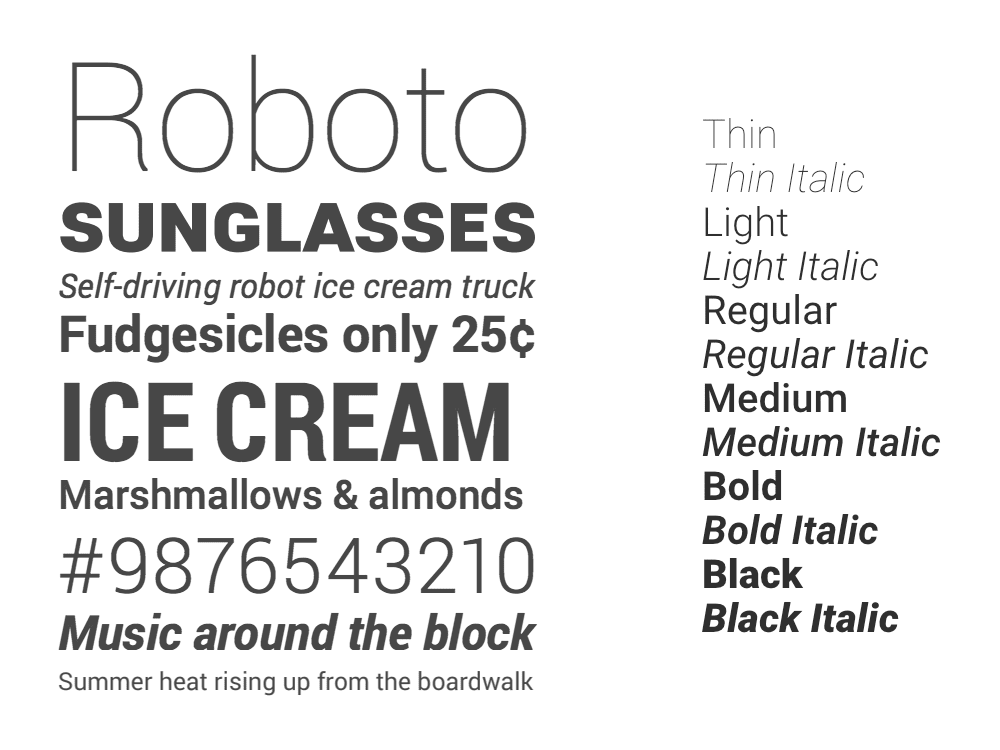
ডিজাইনার এবং বিকাশকারীর জন্য চ্যালেঞ্জ
যখন একজন ডিজাইনার একটি মুদ্রণ প্রকল্প তৈরি করে তখন তারা কিছু সীমাবদ্ধতার সম্মুখীন হয়, যেমন পৃষ্ঠার বিন্যাসের প্রকৃত আকার, তারা কত রং ব্যবহার করতে পারে (যা ব্যবহার করা হবে এমন প্রিন্টিং প্রেস দ্বারা নির্ধারিত হয়) ইত্যাদি। কিন্তু তারা যত খুশি টাইপফেস শৈলী ব্যবহার করতে পারে। এর মানে হল যে প্রিন্ট মিডিয়ার টাইপোগ্রাফি প্রায়শই সমৃদ্ধ এবং পরিশীলিত হয়, যাতে পড়ার অভিজ্ঞতা সত্যিই আনন্দদায়ক হয়। শেষবার আপনি একটি চমৎকার ম্যাগাজিন ব্রাউজিং উপভোগ করেছেন তা চিন্তা করুন।
ওয়েব ডিজাইনার এবং ডেভেলপারদের প্রিন্ট ডিজাইনারদের তুলনায় বিভিন্ন সীমাবদ্ধতা রয়েছে এবং একটি গুরুত্বপূর্ণ হল আমাদের ডিজাইনের সাথে সম্পর্কিত ব্যান্ডউইথ খরচ। এটি আরও সমৃদ্ধ টাইপোগ্রাফিক অভিজ্ঞতার জন্য একটি স্টিকিং পয়েন্ট হয়েছে, কারণ সেগুলি একটি খরচে আসে। ঐতিহ্যগত ওয়েব ফন্টের সাথে, আমাদের ডিজাইনে ব্যবহৃত প্রতিটি শৈলীর জন্য ব্যবহারকারীদের একটি পৃথক ফন্ট ফাইল ডাউনলোড করতে হবে, যা লেটেন্সি এবং পৃষ্ঠা রেন্ডারিং সময় বাড়ায়। শুধুমাত্র রেগুলার এবং বোল্ড স্টাইল সহ তাদের তির্যক সমকক্ষ সহ, ফন্ট ডেটার পরিমাণ 500 KB বা তার বেশি হতে পারে। ফন্টগুলি কীভাবে রেন্ডার করা হয়, আমাদের যে ফলব্যাক প্যাটার্নগুলি ব্যবহার করতে হবে, বা FOIT এবং FOUT-এর মতো অবাঞ্ছিত পার্শ্ব-প্রতিক্রিয়াগুলি নিয়ে কাজ করার আগেও এটি।
অনেক ফন্ট পরিবার অনেক বিস্তৃত শৈলী অফার করে, পাতলা থেকে কালো ওজন, সংকীর্ণ এবং প্রশস্ত প্রস্থ, বিভিন্ন শৈলীগত বিবরণ এবং এমনকি আকার-নির্দিষ্ট ডিজাইন (বড় বা ছোট পাঠের আকারের জন্য অপ্টিমাইজ করা।) যেহেতু আপনাকে প্রতিটি শৈলীর জন্য একটি নতুন ফন্ট ফাইল লোড করতে হবে (অথবা শৈলীর সংমিশ্রণ), অনেক ওয়েব বিকাশকারী তাদের এই ক্ষমতাগুলিকে পুনরায় ব্যবহার করতে পছন্দ করে না।
একটি পরিবর্তনশীল ফন্টের অ্যানাটমি
ভেরিয়েবল ফন্ট এই চ্যালেঞ্জগুলিকে মোকাবেলা করে, একটি একক ফাইলে শৈলী প্যাক করে।
এটি একটি কেন্দ্রীয় বা 'ডিফল্ট' শৈলী দিয়ে শুরু করে কাজ করে, সাধারণত 'নিয়মিত'–একটি সোজা রোমান নকশা যার সবচেয়ে সাধারণ ওজন এবং প্রস্থ যা প্লেইন টেক্সটের জন্য সবচেয়ে উপযুক্ত। এটি তখন একটি অবিচ্ছিন্ন পরিসরে অন্যান্য শৈলীর সাথে সংযুক্ত থাকে, যাকে বলা হয় 'অক্ষ'। সবচেয়ে সাধারণ অক্ষ হল ওজন , যা একটি বোল্ড শৈলীর মাধ্যমে ডিফল্ট শৈলীকে সংযুক্ত করতে পারে। যেকোন স্বতন্ত্র শৈলী একটি অক্ষ বরাবর অবস্থিত হতে পারে এবং একে ভেরিয়েবল ফন্টের 'ইনস্ট্যান্স' বলা হয়। কিছু উদাহরণ ফন্ট ডেভেলপার দ্বারা নামকরণ করা হয়, উদাহরণস্বরূপ ওজন অক্ষ অবস্থান 600 বলা হয় SemiBold.
পরিবর্তনশীল ফন্ট Roboto Flex এর ওজন অক্ষের জন্য তিনটি শৈলী রয়েছে। নিয়মিত শৈলী কেন্দ্রে থাকে এবং অক্ষের বিপরীত প্রান্তে দুটি শৈলী রয়েছে, একটি হালকা এবং অন্যটি ভারী। এইগুলির মধ্যে, আপনি 900টি উদাহরণ থেকে বেছে নিতে পারেন:
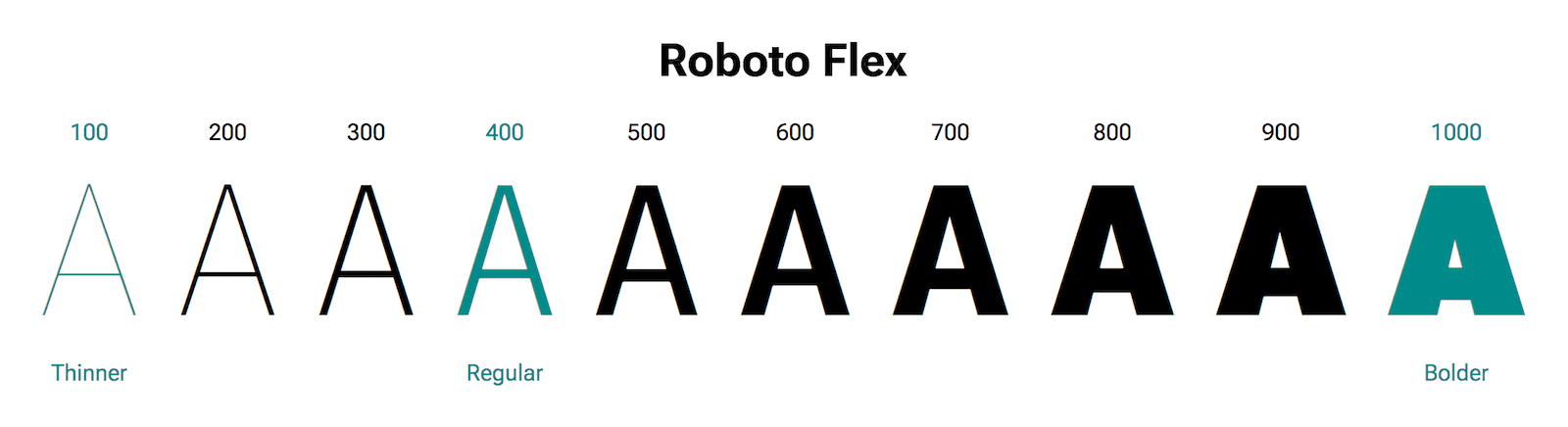
ফন্ট বিকাশকারী বিভিন্ন অক্ষের একটি সেট অফার করতে পারে। আপনি তাদের একত্রিত করতে পারেন কারণ তারা সবাই একই ডিফল্ট শৈলী ভাগ করে। রোবোটোর একটি প্রস্থের অক্ষে তিনটি শৈলী রয়েছে: নিয়মিতটি অক্ষের কেন্দ্রে থাকে এবং দুটি শৈলী, সংকীর্ণ এবং চওড়া, প্রতিটি প্রান্তে থাকে। এগুলি নিয়মিত শৈলীর সমস্ত প্রস্থ প্রদান করে এবং ওজন অক্ষের সাথে একত্রিত করে প্রতিটি ওজনের জন্য সমস্ত প্রস্থ প্রদান করে।
এর মানে হাজার হাজার স্টাইল আছে! এটি বিশাল ওভারকিলের মতো মনে হতে পারে, তবে এই ধরণের শৈলীর বৈচিত্র্য দ্বারা পড়ার অভিজ্ঞতার গুণমান উল্লেখযোগ্যভাবে উন্নত করা যেতে পারে। এবং, যদি এটি পারফরম্যান্স পেনাল্টি ছাড়া হয়, ওয়েব ডেভেলপাররা তাদের ইচ্ছামত কয়েকটি বা যতগুলি স্টাইল ব্যবহার করতে পারে-এটি তাদের ডিজাইনের উপর নির্ভর করে।
তির্যক
পরিবর্তনশীল ফন্টে ইটালিকগুলি যেভাবে পরিচালনা করা হয় তা আকর্ষণীয়, কারণ দুটি পার্থক্য পদ্ধতি রয়েছে। হেলভেটিকা বা রোবোটোর মতো টাইপফেসগুলিতে ইন্টারপোলেশন সামঞ্জস্যপূর্ণ কনট্যুর রয়েছে, তাই তাদের রোমান এবং ইটালিক শৈলীগুলির মধ্যে ইন্টারপোলেট করা যেতে পারে এবং রোমান থেকে ইটালিকে যাওয়ার জন্য স্ল্যান্ট অক্ষ ব্যবহার করা যেতে পারে।
অন্যান্য টাইপফেসে (যেমন গ্যারামন্ড, বাস্কেরভিল বা বোডোনি) রোমান এবং ইটালিক গ্লাইফ কনট্যুর রয়েছে যা ইন্টারপোলেশন সামঞ্জস্যপূর্ণ নয়। উদাহরণস্বরূপ, যে কনট্যুরগুলি সাধারণত একটি রোমান ছোট হাতের "n" সংজ্ঞায়িত করে তা একটি ইটালিক ছোট হাতের "n" সংজ্ঞায়িত করতে ব্যবহৃত কনট্যুরগুলির সাথে মেলে না। একটি কনট্যুর অন্য কনট্যুরকে ইন্টারপোলেট করার পরিবর্তে, ইটালিক অক্ষ রোমান থেকে ইটালিক কনট্যুরগুলিতে টগল করে।
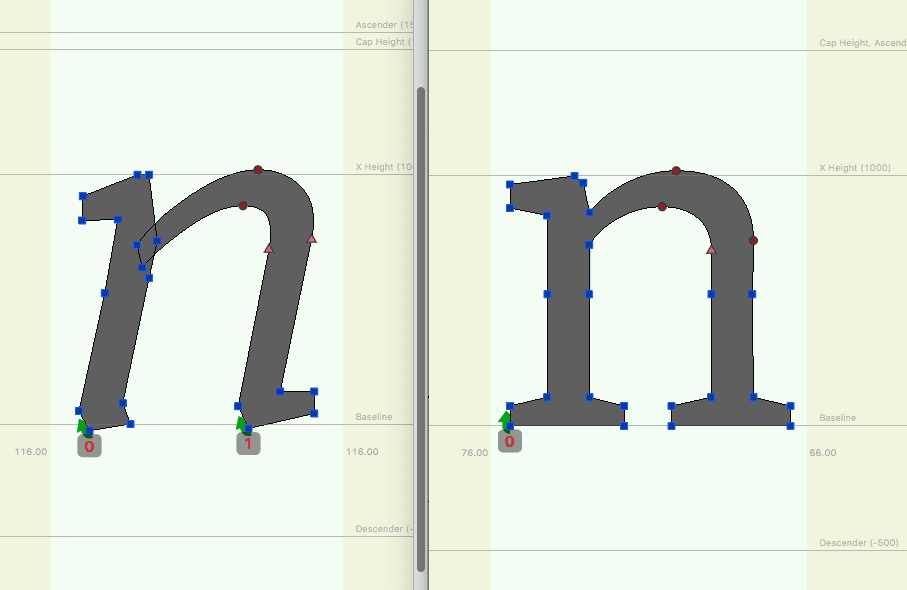
ইটালিক-এ স্যুইচ করার পরে, ব্যবহারকারীর কাছে উপলব্ধ অক্ষগুলি রোমানদের জন্য একই হওয়া উচিত, ঠিক যেমন অক্ষর সেটটি একই হওয়া উচিত।